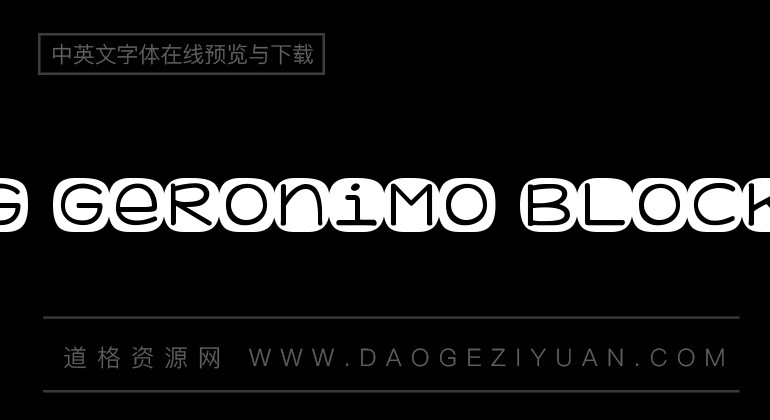
KG Geronimo Blocks
KG Geronimo Blocks 是一种极具特色的字体,它的设计特点是结合了手写和印刷的风格。它的字母形状带有些微的不规则和手工的感觉,同时也有一些像印刷体的笔画粗细和黑度变化。这种字体适合用于各种创意设计和印刷品制作,比如海报、贺卡、标语、广告等。 KG Geronimo Blocks 字体的设计师是 Kimmy Design,这是一个专门从事字体设计的工作室,他们的字体作品广受欢迎,尤其以手写风格的字体著称。KG Geronimo Blocks 字体的命名灵感来自于一位美国印第安人,传说中他是一个勇敢的领袖和战士。 KG Geronimo Blocks 字体包括了大写字母、小写字母、数字和一些特殊符号,可以在许多设计软件和应用程序中使用,比如 Adobe Photoshop、Illustrator、InDesign 等等。由于它的设计独特且易于辨认,因此也经常被用于商业品牌的设计和标志制作。
KG Geronimo Blocks是一款非常不错的手写艺术字体,具有很好的视觉感,适合于文化类的宣传设计、商业类品牌的广告和产品包装设计以及个性化文字排版等较多场景。